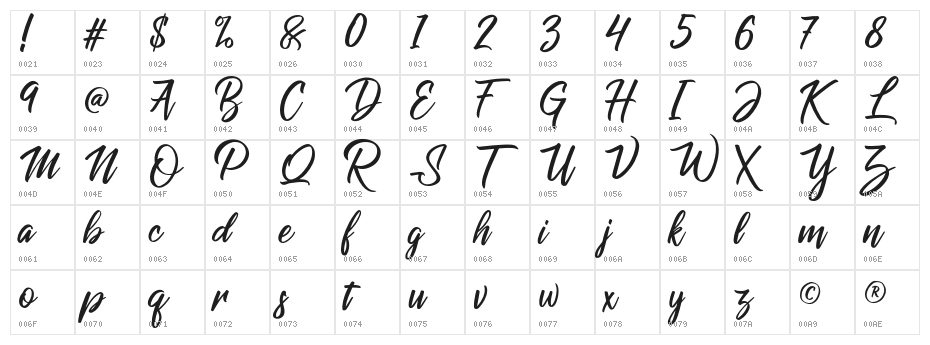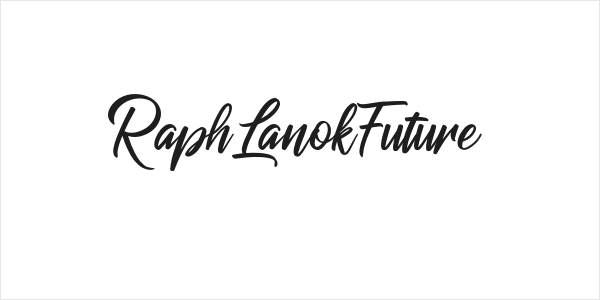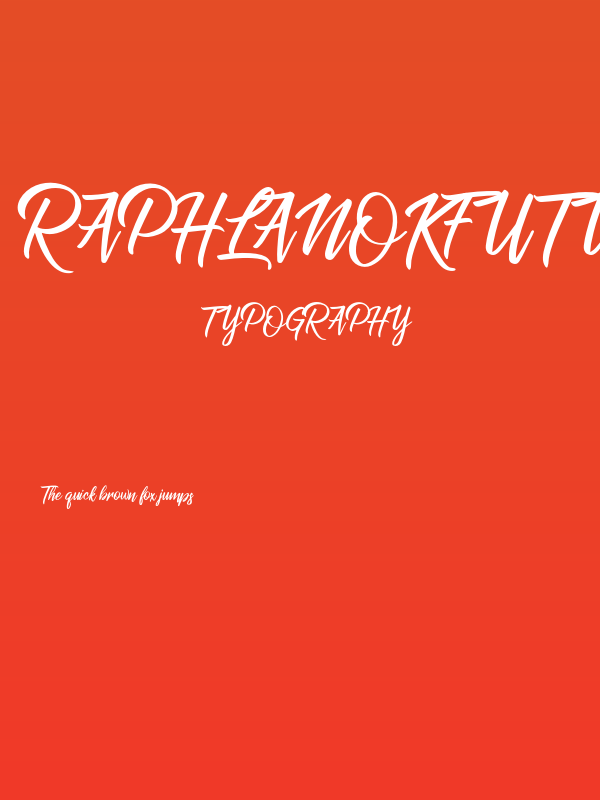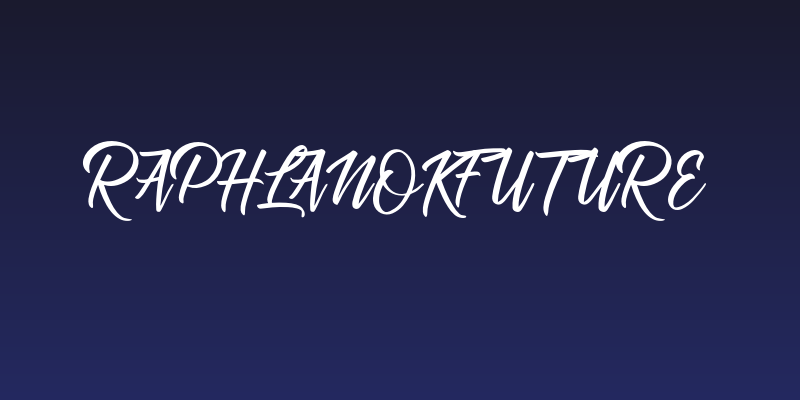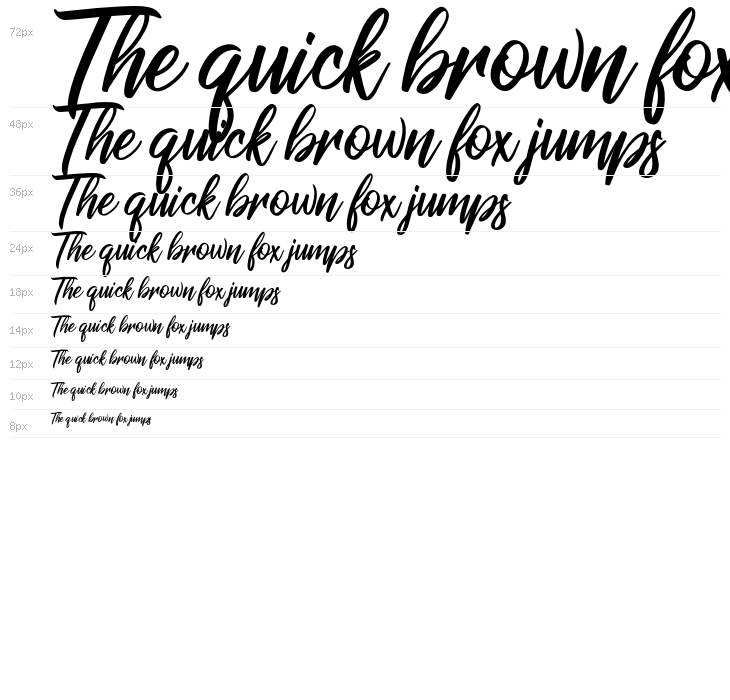
RaphLanokFuture Font
| Caso d'uso | Logos, Invitations, Branding |
| Progetti proposti | Ideal for wedding invitations, branding, greeting cards, and elegant packaging designs. |